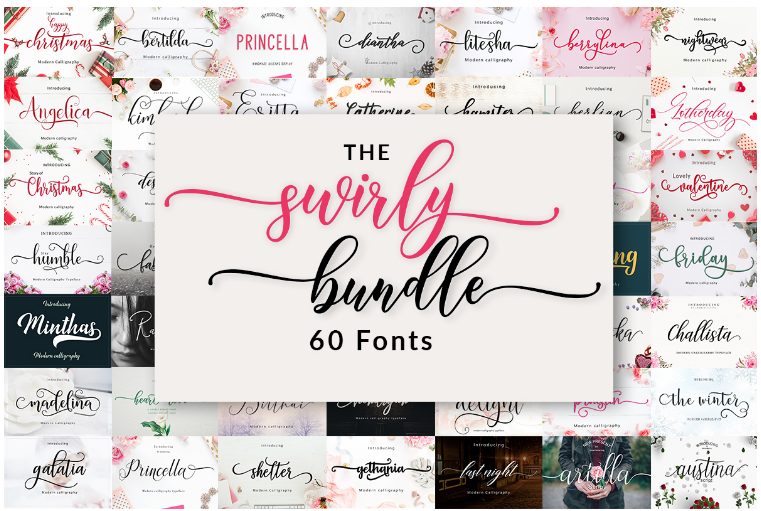
[Creativefabrica] The Swirly Fonts Bundle (Amarlettering)
В пакет Swirly Fonts Bundle входят 60 элегантных семейств шрифтов, которые удовлетворят все ваши потребности в рукоделии! Большинство из этих шрифтов закодированы PUA, что означает, что они содержат великолепные вихревые дополнительные символы.